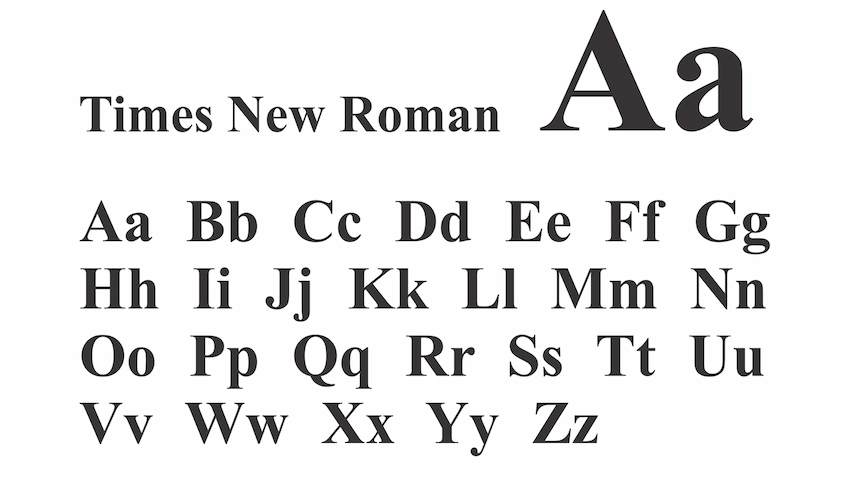
Font Times New Roman là một trong những loại font chữ phổ biến nhất trên toàn cầu, được sử dụng rộng rãi trong nhiều lĩnh vực khác nhau. Với thiết kế lịch sự và dễ đọc, Font Times New Roman đã trở thành lựa chọn hàng đầu cho rất nhiều tài liệu, bài báo, và các tác phẩm văn học. Bài viết này Mạnh An Trà sẽ giúp bạn hiểu rõ hơn về quá trình hình thành, ứng dụng, cách tải và cài đặt cũng như so sánh với các font chữ khác.
Giới thiệu về Font Times New Roman
Trước khi đi sâu vào chi tiết, chúng ta cần biết rằng Font Times New Roman không chỉ đơn thuần là một kiểu chữ; nó còn mang trong mình câu chuyện lịch sử và văn hóa của thế kỷ 20. Ngày nay, việc sử dụng font chữ này không còn xa lạ mà đã trở thành một phần không thể thiếu trong cuộc sống hàng ngày của chúng ta.
Lịch sử hình thành và phát triển của font Times New Roman
Được thiết kế bởi Stanley Morison cho tờ báo The Times của London vào năm 1931, Font Times New Roman ra đời nhằm mục đích cải thiện độ dễ đọc trong in ấn. Khi đó, Morison nhắm đến việc tạo ra một font chữ có thể tái hiện chính xác nội dung nhưng vẫn đảm bảo tính thẩm mỹ.
Sau khi được giới thiệu, Font Times New Roman nhanh chóng trở nên nổi tiếng và được chấp nhận rộng rãi không chỉ ở Anh mà trên toàn thế giới. Điều này dẫn đến việc font chữ này trở thành một trong những tiêu chuẩn cho các tài liệu văn bản chính thức. Qua thời gian, nó đã trải qua nhiều phiên bản cập nhật để đáp ứng nhu cầu của người dùng hiện đại.
Các ứng dụng phổ biến
Với tính năng dễ đọc và chuyên nghiệp, Font Times New Roman được sử dụng trong nhiều lĩnh vực như:
- Giáo dục: Nhiều trường học và cơ sở giáo dục yêu cầu sinh viên sử dụng font chữ này cho luận văn, báo cáo.
- Kinh doanh: Trong ngành kinh doanh, Font Times New Roman thường được dùng để viết email, báo cáo, hợp đồng vì tính trang trọng của nó.
- Xuất bản: Các nhà xuất bản sách thường chọn font này cho các tác phẩm văn học do khả năng truyền tải cảm xúc mạnh mẽ và dễ tiếp cận với độc giả.
Đặc điểm nổi bật
Font Times New Roman có nhiều đặc điểm nổi bật khiến nó trở thành lựa chọn ưu tiên cho nhiều người:
- Tính dễ đọc: Các ký tự được thiết kế với khoảng cách hợp lý, giúp người đọc dễ dàng theo dõi nội dung.
- Phong cách cổ điển: Với vẻ ngoài thanh lịch, font chữ này phù hợp với phong cách truyền thống, làm tăng giá trị thẩm mỹ cho tài liệu.
- Độ linh hoạt cao: Có thể sử dụng cho nhiều loại văn bản từ thông tin kỹ thuật đến các tác phẩm nghệ thuật.
Sử dụng Font Times New Roman hiệu quả trong thiết kế
Việc sử dụng Font Times New Roman trong thiết kế không chỉ đơn thuần là chọn font cho văn bản. Nó đòi hỏi bạn phải hiểu sâu về cách kết hợp sao cho hài hòa và thu hút.
Lựa chọn kích thước và kiểu chữ phù hợp
Khi làm việc với Font Times New Roman, việc chọn kích thước và kiểu chữ phù hợp là điều rất quan trọng. Nếu bạn đang thiết kế một tài liệu chính thức, hãy sử dụng kích thước từ 12 đến 14 cho văn bản chính.
Thêm vào đó, nếu bạn muốn làm nổi bật một số đoạn văn hoặc tiêu đề, hãy cân nhắc sử dụng kiểu chữ đậm hoặc nghiêng. Điều này không chỉ giúp phân tách nội dung mà còn thu hút sự chú ý của người đọc.
Kết hợp với các font chữ khác
Một trong những yếu tố thú vị trong thiết kế là khả năng kết hợp Font Times New Roman với các font chữ khác. Ví dụ, bạn có thể sử dụng Font Arial cho các tiêu đề và Font Times New Roman cho nội dung chính. Sự kết hợp này không chỉ tạo ra sự đối lập mà còn làm cho tài liệu của bạn trở nên phong phú hơn.
Hãy luôn nhớ rằng sự cân bằng là rất quan trọng. Đừng nên sử dụng quá nhiều font chữ khác nhau trong một tài liệu, vì điều này có thể gây rối mắt cho người đọc.
Cách sử dụng font trong tài liệu văn bản và trình bày
Khi sử dụng Font Times New Roman trong tài liệu văn bản, hãy chắc chắn rằng bạn duy trì sự nhất quán trong toàn bộ tài liệu. Điều này có nghĩa là bạn nên sử dụng cùng một kích thước và kiểu chữ cho tất cả các phần tương tự.